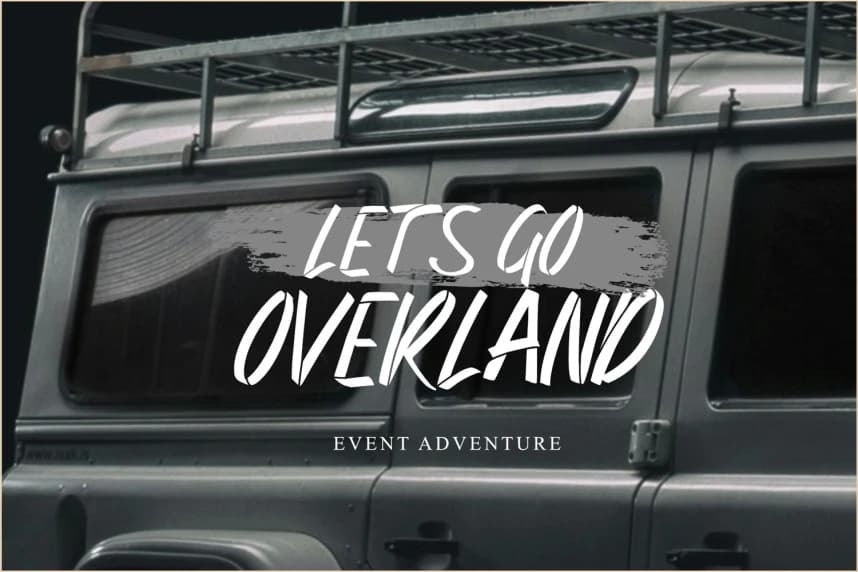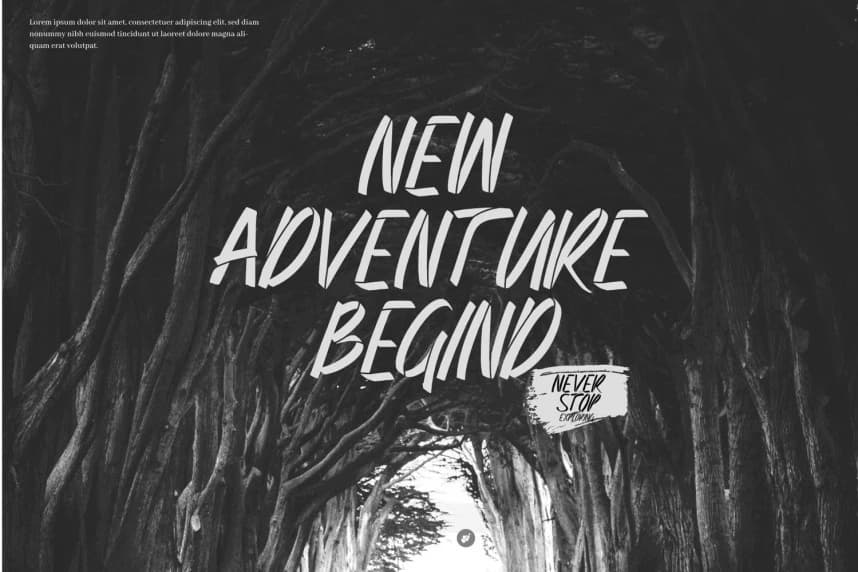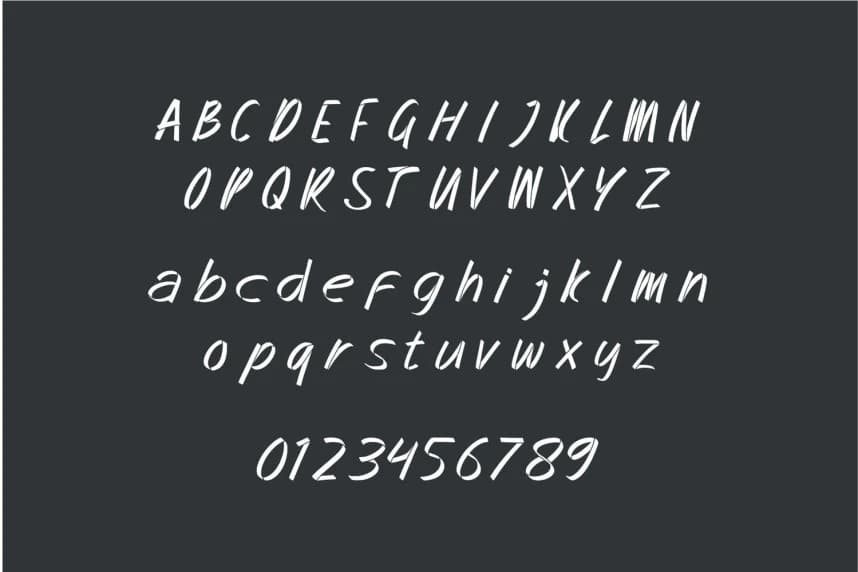
Redesign Stencil Font
Redesign Stencil Font - Brush Stencil Font, sert stencil kesimiyle birleşmiş kaba fırça darbesi stilinde bir yazı tipi olup güçlü, cesur ve ifadeli bir harf karakteri yaratır. Bu yazı tipi, sokak, asi ve modern görselleri tek bir tipografik dokunuşla göstermek isteyenler için tasarlanmıştır.